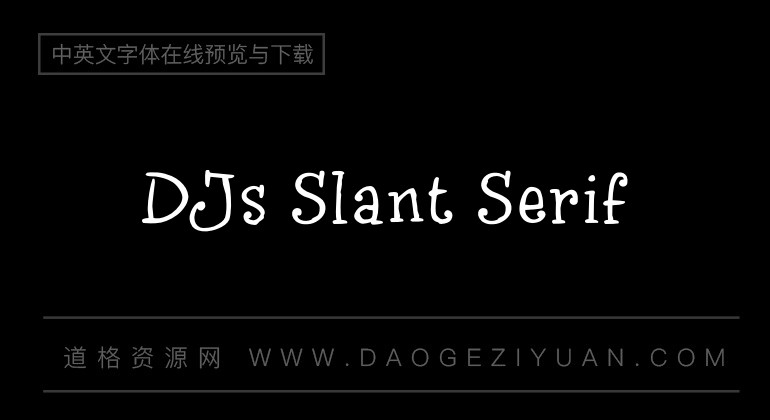
DJs Slant Serif
DJs Slant Serif是一款由著名设计师Dave Jarvis设计的斜体衬线字体,它结合了文本和衬线字体的特点,以及新颖的设计,可以满足您的多种字体需求。它具有非常精致的曲线,清晰的衬线,宽大的空间,以及鲜明的字形,可以为您的文本提供更多的视觉冲击力。此外,它还有多种字重,可以满足您的不同需求。DJs Slant Serif字体可以用于各种类型的文本,包括印刷和网页,能够提供更多的灵活性和可读性,可以让您的文本更加出彩。
DJs Slant Serif是一款非常不错的手写艺术字体,具有很好的视觉感,适合于文化类的宣传设计、商业类品牌的广告和产品包装设计以及个性化文字排版等较多场景。
DJs Slant Serif字符映射图